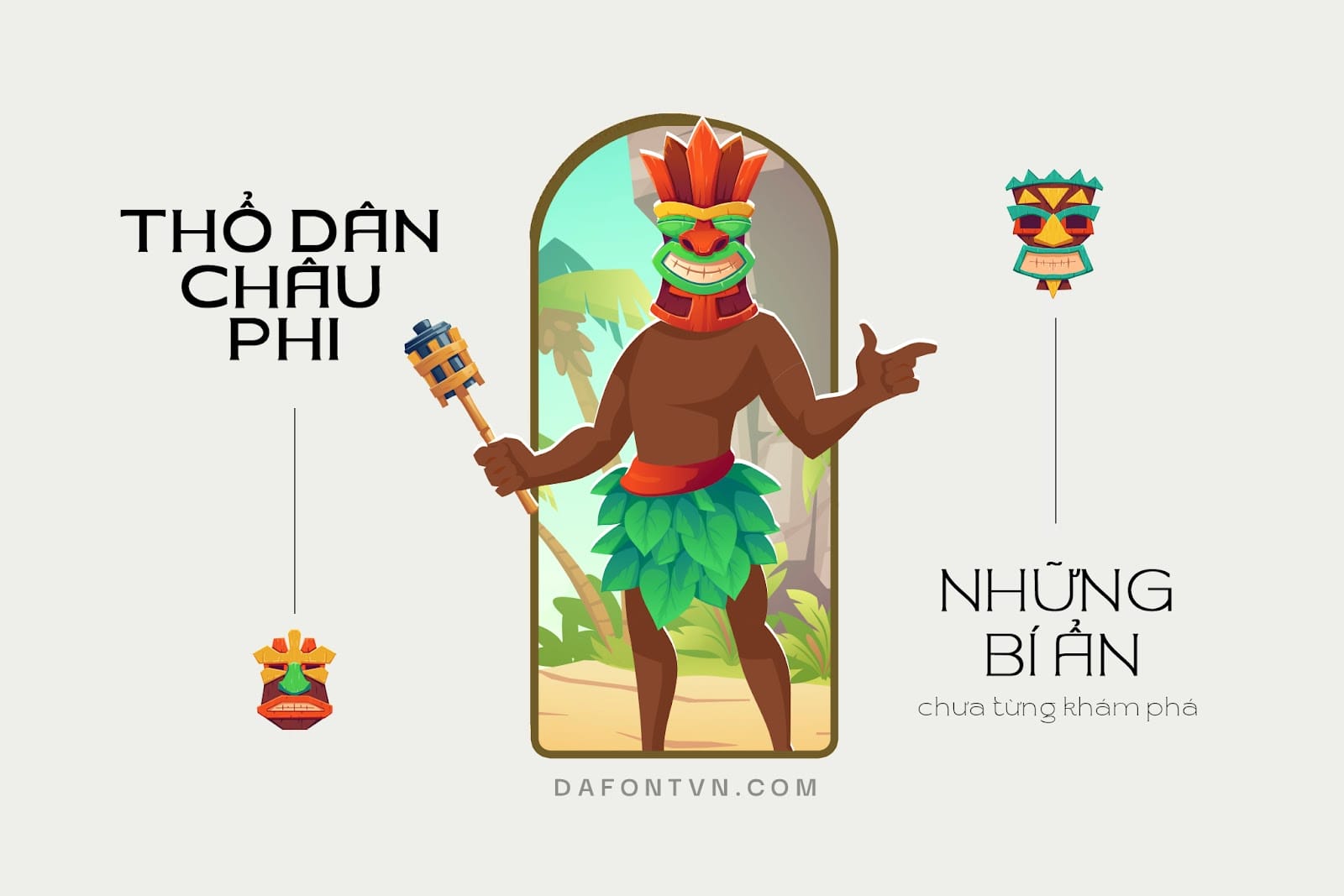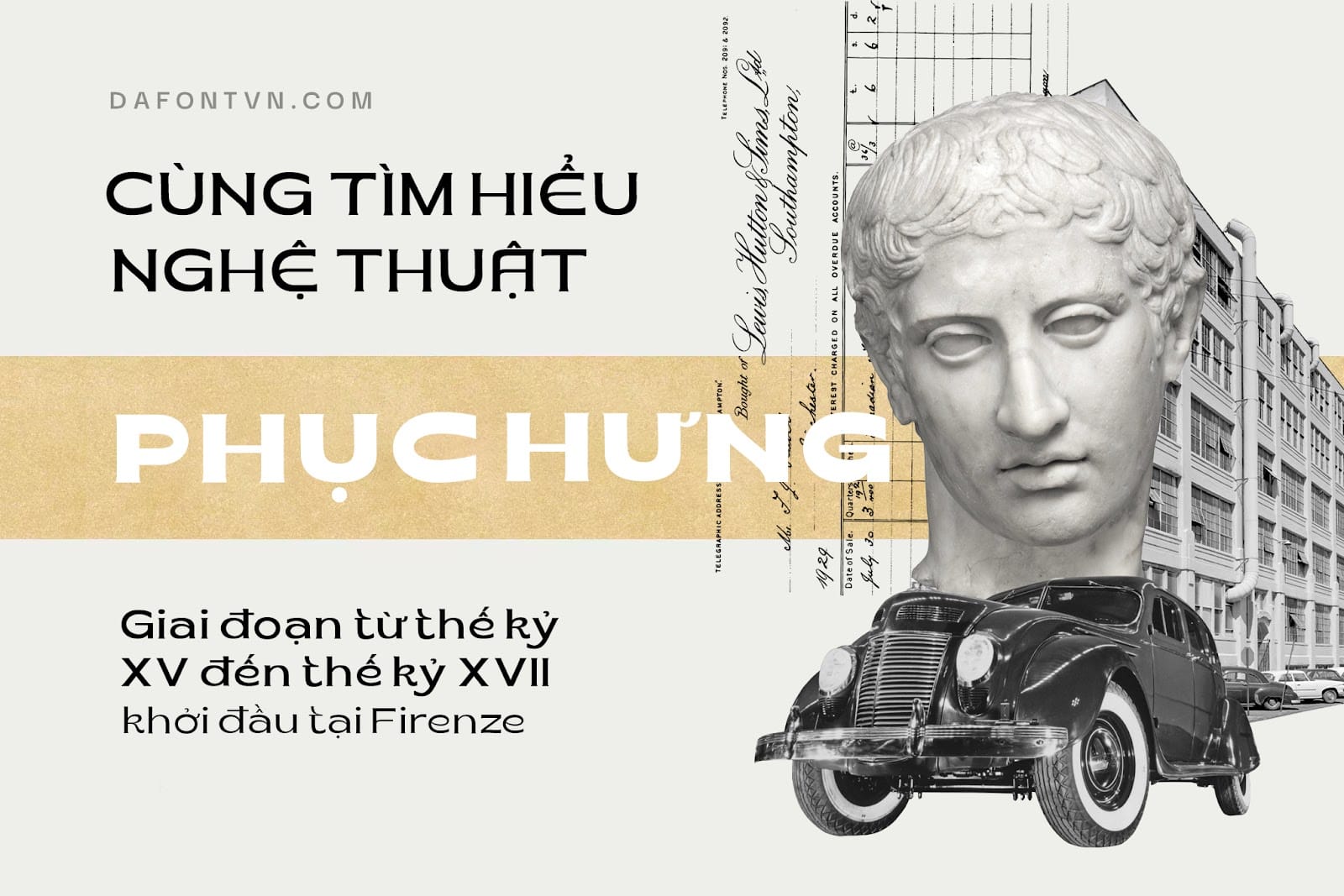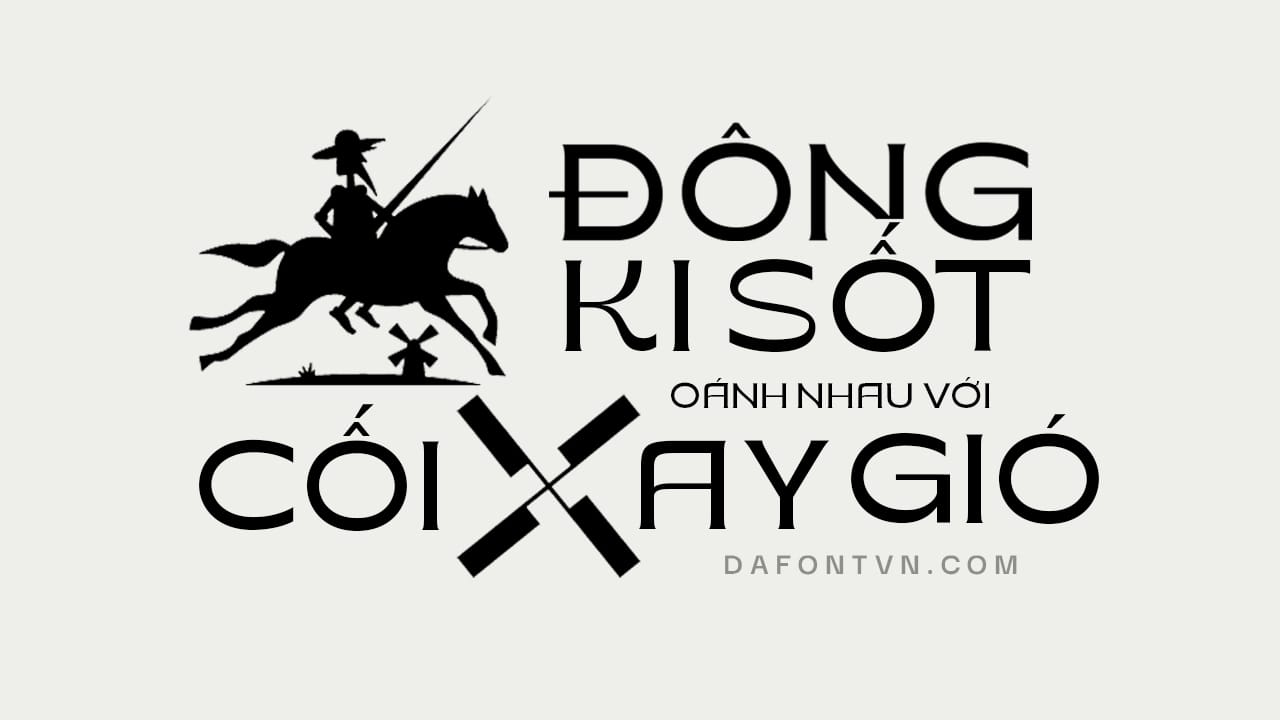
Konde Typeface được thiết kế mang phong cách retro với các nét chữ ấn tượng phù hợp cho rất nhiều các thiết kế khác nhau như tiêu đề văn bản, bìa sách và các thiết kế hướng đến sự cổ điển, ngoài ra, font Konde cũng rất tốt để sử dụng cho văn bản nội dung. Font Konde có 3 kiểu từ Thin đến Black để bạn có thể sử dụng cho nhiều nội dung khác nhau.Kiểu chữ Konde rất dễ để sử dụng cho các thiết kế cổ điển và hoài cổ, bên cạnh đó font có tới 594 glyph với nhiều tùy chọn độc đáo và thú vị vì vậy bạn có thể sử dụng nó để biến đổi các ký tự khác nhau để làm cho các thiết kế thêm phong phú hơn.